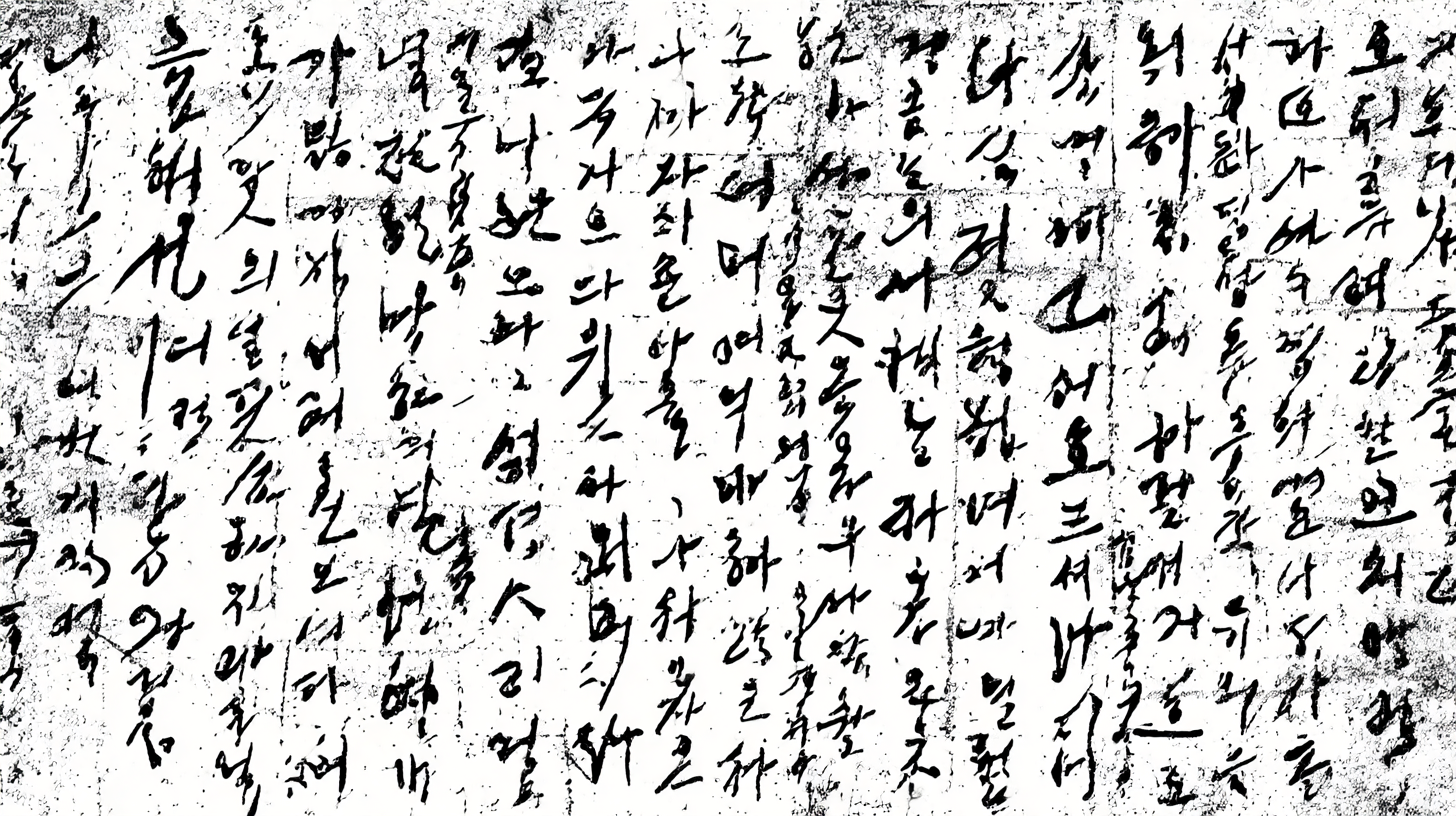
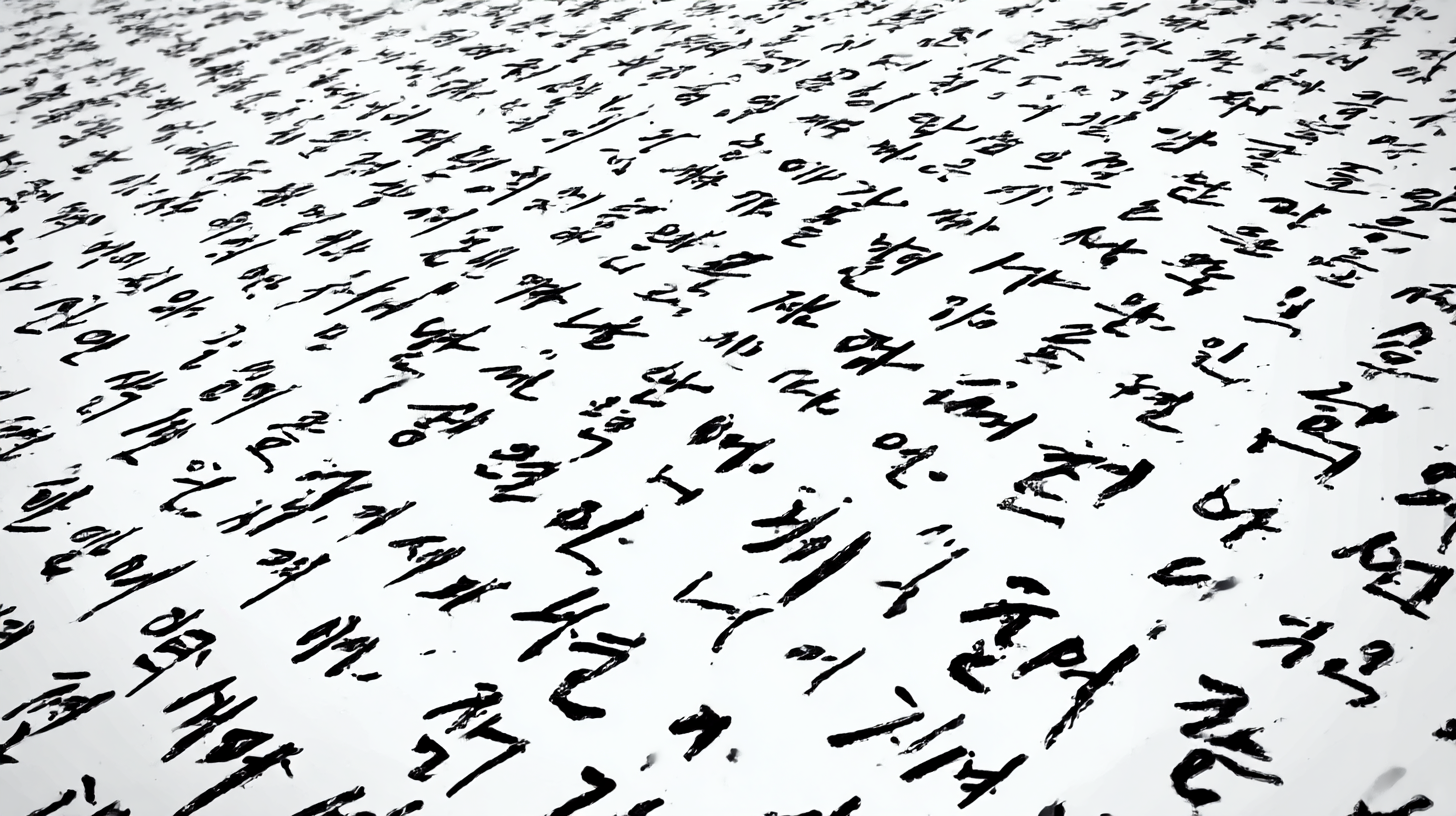
✍ 가독성이 높은 글씨체는 읽기 편하고 정리된 느낌을 주는 글씨예요. 시험 필기, 업무 기록, 다이어리 정리 등 다양한 상황에서 가독성 높은 글씨는 큰 도움이 된답니다! 🔍📖
내가 생각했을 때 가독성 좋은 글씨체는 꾸준한 연습과 몇 가지 핵심 요소만 신경 쓰면 누구나 만들 수 있어요! 오늘은 초보자도 쉽게 따라 할 수 있도록 가독성 높은 글씨체를 만드는 방법을 알려드릴게요. 🖊🔥
📖 가독성 높은 글씨체의 중요성
가독성이 좋은 글씨체는 단순히 보기 좋은 글씨가 아니라, 읽기 쉽고 이해하기 쉬운 글씨를 의미해요. 특히 노트 필기, 문서 작성, 다이어리 정리 등에서 가독성이 높으면 내용을 빠르게 파악할 수 있답니다. 🖊✨
다음과 같은 이유로 가독성이 높은 글씨체를 연습하는 것이 중요해요.
- 📖 이해력 향상 - 정돈된 글씨는 내용을 쉽게 파악할 수 있음
- ⏳ 복습 효율 증가 - 읽기 쉬운 필기는 복습 시간을 단축시킴
- 📝 노트 정리 최적화 - 깔끔한 필기로 정보 정리 능력 향상
- 📑 전달력 향상 - 가독성 높은 글씨는 상대방이 이해하기 쉬움
📊 가독성이 높은 글씨 vs 낮은 글씨 비교
구분 가독성이 높은 글씨 가독성이 낮은 글씨 글씨 크기 균일하고 일정함 불규칙하고 크기 차이가 큼 자간(글자 간격) 균일하게 정렬됨 너무 좁거나 넓음 행간(줄 간격) 적절한 여백 유지 줄이 겹쳐 읽기 어려움 이처럼 가독성이 높은 글씨는 읽기 쉽고 정리된 느낌을 주는 반면, 가독성이 낮으면 정보를 이해하기 어렵게 만들어요. 이제 가독성을 결정하는 주요 요소를 알아볼까요? 🔍
🔎 가독성을 결정하는 요소
가독성이 좋은 글씨를 만들기 위해서는 일정한 규칙과 몇 가지 요소를 신경 써야 해요. 글씨가 예쁘더라도 읽기 어려우면 실용성이 떨어지기 때문에, 가독성을 높이는 핵심 요소를 체크해보세요! 📝✨
📌 가독성을 높이는 5가지 요소
요소 설명 1. 글씨 크기 글씨 크기가 너무 크거나 작으면 읽기 어려워요. 적절한 크기를 유지하세요. 2. 자간(글자 간격) 글자 간격이 너무 좁거나 넓으면 가독성이 떨어져요. 균형 잡힌 자간이 중요해요. 3. 행간(줄 간격) 줄 간격이 너무 좁으면 글자가 겹쳐 보일 수 있어요. 일정한 행간을 유지하세요. 4. 획 정리 획이 엉성하거나 번지면 글씨가 흐려져요. 또박또박 선을 정리하세요. 5. 정렬 방식 글씨가 기울어지거나 일정하지 않으면 가독성이 낮아져요. 정렬을 맞춰보세요. 이 5가지 요소를 신경 쓰면서 글씨를 연습하면 자연스럽게 가독성이 높아질 거예요! 이제 구체적인 가독성 높은 글씨체 연습법을 배워볼까요? ✍
✍ 가독성 높은 글씨체 연습법
가독성이 높은 글씨체를 만들려면 단계적으로 연습하는 것이 중요해요. 처음부터 글씨를 예쁘게 쓰려고 하기보다는, 기초적인 연습을 차근차근 따라가는 것이 더 효과적이랍니다! 📖✨
📌 가독성을 높이는 단계별 연습법
연습 단계 설명 추천 도구 1단계: 선 연습 직선, 곡선, 점선 등 다양한 선을 일정하게 그려보세요. 연필, 모눈 노트 2단계: 글자 크기 맞추기 모든 글자의 크기를 일정하게 유지하면서 써보세요. 도트 그리드 노트 3단계: 글자 간격 조절 자간을 균일하게 유지하는 연습을 해보세요. 모눈 노트, 줄 노트 4단계: 단어 & 문장 쓰기 연습한 글씨를 활용해 단어와 문장을 써보세요. 젤펜, 만년필 이 단계를 따라가면 자연스럽게 글씨가 정돈되고, 읽기 편한 글씨체가 완성될 거예요! ✨ 이제 가독성이 좋은 추천 글씨체 스타일도 함께 살펴볼까요? 🖊
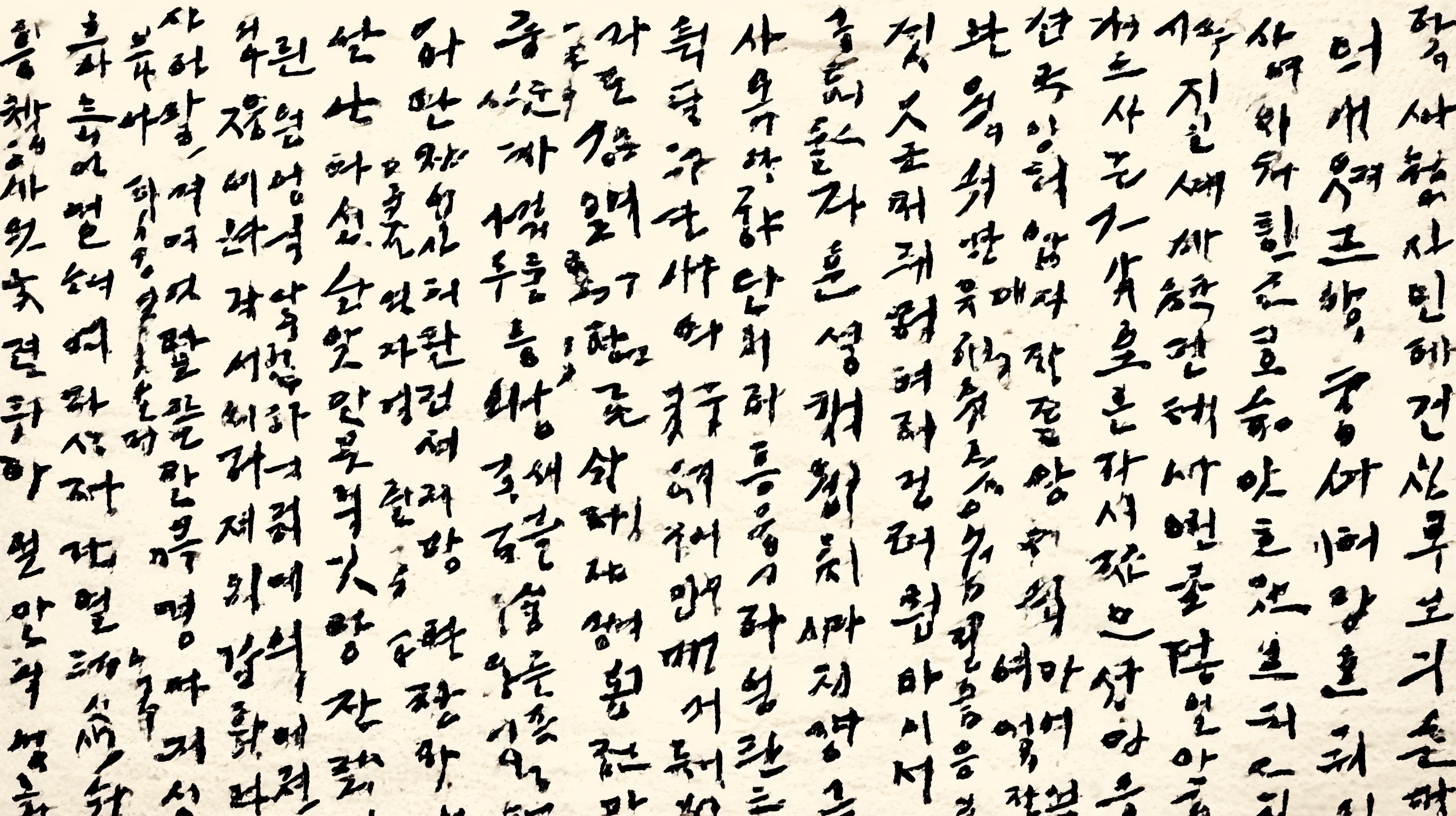
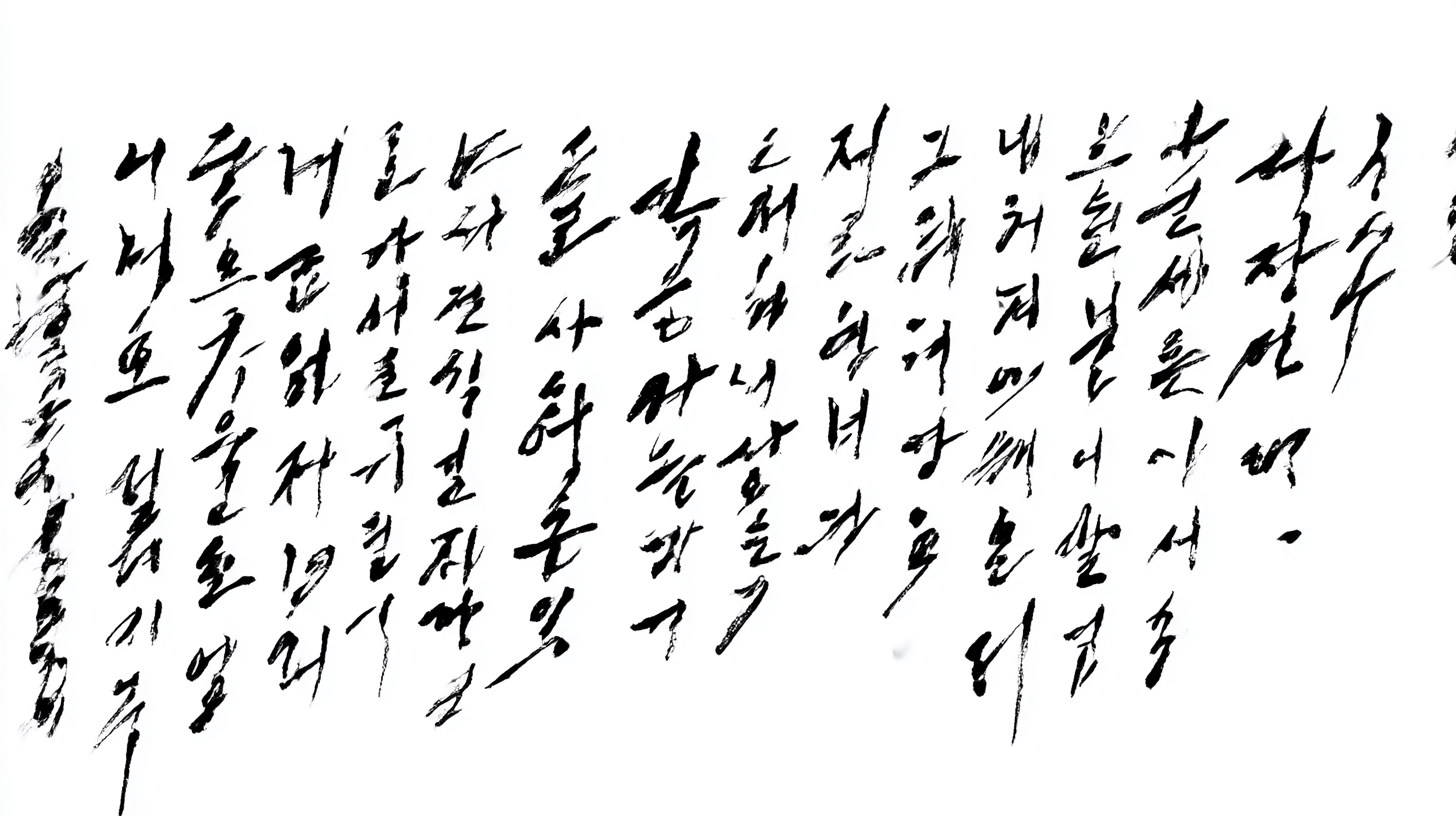
가독성 높은 글씨체 연습법 📖 추천하는 가독성 좋은 글씨체 스타일
가독성이 좋은 글씨체는 글자 간격이 균형 잡히고, 선이 명확한 스타일이 많아요. 글씨체의 종류에 따라 느낌이 달라지기 때문에, 본인의 필기 스타일과 목적에 맞는 글씨체를 선택하는 것이 중요해요! ✍✨
📌 가독성이 뛰어난 대표 글씨체 비교
글씨체 스타일 특징 추천 용도 🖊 정자체 획이 일정하고 단정한 글씨체 시험 필기, 업무 노트 ✏ 모던 둥근 글씨 부드럽고 따뜻한 느낌의 둥근 글씨체 다이어리, 감성 노트 📝 깔끔한 흘림체 자연스럽게 이어지는 필기체 속기 필기, 노트 정리 📄 서류용 글씨체 획이 분명하고 공식 문서에 적합한 스타일 공문서, 보고서 작성 가독성이 높은 글씨체를 선택하면 필기 시간이 단축되고, 나중에 다시 볼 때도 훨씬 정리가 잘 되어 보이는 효과가 있어요! 📖✨ 이제 가독성 높은 필기를 돕는 추천 필기구도 알아볼까요? 🖋
🖊 가독성 높은 필기를 위한 필기구 추천
가독성이 좋은 글씨를 쓰려면 적절한 필기구를 선택하는 것이 중요해요! 필기감이 부드럽고 선명한 펜을 사용하면, 손에 힘을 덜 주고도 또렷한 글씨를 쓸 수 있답니다. ✍✨
📌 가독성 높은 필기를 위한 추천 필기구
필기구 특징 추천 용도 유니볼 시그노 0.38 얇고 선명한 필기감 정자체, 시험 필기 펜텔 에너겔 0.5 부드럽고 빠른 필기 가능 흘림체, 빠른 노트 정리 프릭션 볼펜 지우개 기능이 있어 수정 가능 초안 필기, 다이어리 정리 텀보우 후데노스케 필압 조절이 쉬운 붓펜 캘리그래피, 꾸미기 필기 📒 필기체 연습에 적합한 노트 추천
노트 종류 특징 추천 필기 스타일 모눈 노트 균형 잡힌 글씨 연습 가능 정자체, 가독성 훈련 도트 그리드 노트 획 정렬을 쉽게 도와줌 흘림체, 노트 정리 무지 노트 자유로운 필기가 가능 캘리그래피, 감성 필기 필기구와 노트를 잘 선택하면 가독성 높은 필기를 더욱 쉽게 연습할 수 있어요! 📖✨ 이제 가독성을 높이는 실전 꿀팁도 함께 알아볼까요? 🖊
💡 가독성을 높이는 실전 꿀팁
가독성이 좋은 글씨를 쓰려면 단순히 글씨를 또박또박 쓰는 것만으로는 부족해요! 몇 가지 필기 습관을 개선하면 더욱 깔끔하고 읽기 쉬운 글씨체를 만들 수 있답니다. ✍✨
📌 가독성을 향상시키는 5가지 필기 습관
꿀팁 설명 1. 일정한 글씨 크기 유지 글자의 높이와 너비를 일정하게 맞추면 가독성이 좋아져요. 2. 자간 & 행간 균일하게 조절 글자 간격과 줄 간격이 일정하면 정리된 느낌을 줄 수 있어요. 3. 손목 힘 빼기 손목에 힘이 들어가면 글씨가 뻣뻣해져요. 부드럽게 움직이세요! 4. 필기 속도 조절 너무 빠르게 쓰면 글씨가 흐트러질 수 있으니 천천히 연습하세요. 5. 가이드라인 활용 모눈 노트나 도트 노트를 사용하면 글씨 정렬이 쉬워요. 이 팁들을 적용하면 더욱 깔끔하고 정돈된 필기체를 완성할 수 있어요! 🎨 이제 필기와 가독성에 대한 자주 묻는 질문(FAQ)을 확인해볼까요? 🤔
Q1. 글씨를 예쁘게 쓰려면 하루에 얼마나 연습해야 하나요?
A1. 하루 10~15분씩 꾸준히 연습하는 것이 좋아요! 짧더라도 매일 연습하면 손에 익숙해져 자연스럽게 글씨가 예뻐진답니다. ✍✨
Q2. 필기 속도를 높이면서도 가독성을 유지하는 방법이 있나요?
A2. 필기 속도를 높이려면 키워드 중심으로 적고, 획을 단순화하는 것이 좋아요. 또한, 연습할 때는 먼저 천천히 또박또박 쓰는 연습을 한 후 점차 속도를 높여보세요. ⏳
Q3. 글씨가 삐뚤어지는 걸 방지하려면 어떻게 해야 하나요?
A3. 줄이 있는 노트를 활용하고, 손목에 힘을 빼면서 천천히 써보세요. 모눈 노트나 도트 그리드 노트를 활용하면 글씨 정렬에 도움이 돼요! 📏
Q4. 가독성이 좋은 글씨체를 연습할 때 가장 중요한 것은?
A4. 일정한 크기, 자간(글자 간격), 행간(줄 간격)을 맞추는 것이 가장 중요해요. 글자마다 크기가 다르면 정리가 안 된 느낌이 들 수 있어요! 🔍
Q5. 어떤 필기구를 사용하면 가독성이 좋아지나요?
A5. 유니볼 시그노 0.38, 펜텔 에너겔 0.5 같은 얇고 선명한 펜이 가독성이 높은 필기에 좋아요. 번짐이 적고 또렷한 필기감을 제공하는 펜을 선택하세요! 🖊
Q6. 손이 떨려서 글씨가 고르지 않아요. 해결 방법이 있을까요?
A6. 손목에 힘을 너무 주지 말고, 편안한 자세로 필기하는 것이 중요해요. 또한, 처음에는 천천히 또박또박 쓰는 연습을 하면 손의 긴장이 풀려요. 🎨
Q7. 필기할 때 글씨 크기를 일정하게 맞추는 방법은?
A7. 모눈 노트나 도트 노트를 활용하면 일정한 크기의 글씨를 연습하는 데 도움이 돼요. 손글씨 가이드라인을 활용하는 것도 효과적인 방법이에요! 📏
Q8. 디지털 필기와 손글씨 중 어떤 것이 더 효과적인가요?
A8. 손글씨는 기억력 향상에 도움이 되고, 디지털 필기는 정리와 보관이 편리해요. 본인의 목적에 맞춰 두 가지 방식을 적절히 혼합해서 사용하는 것이 가장 좋아요! 💻📝